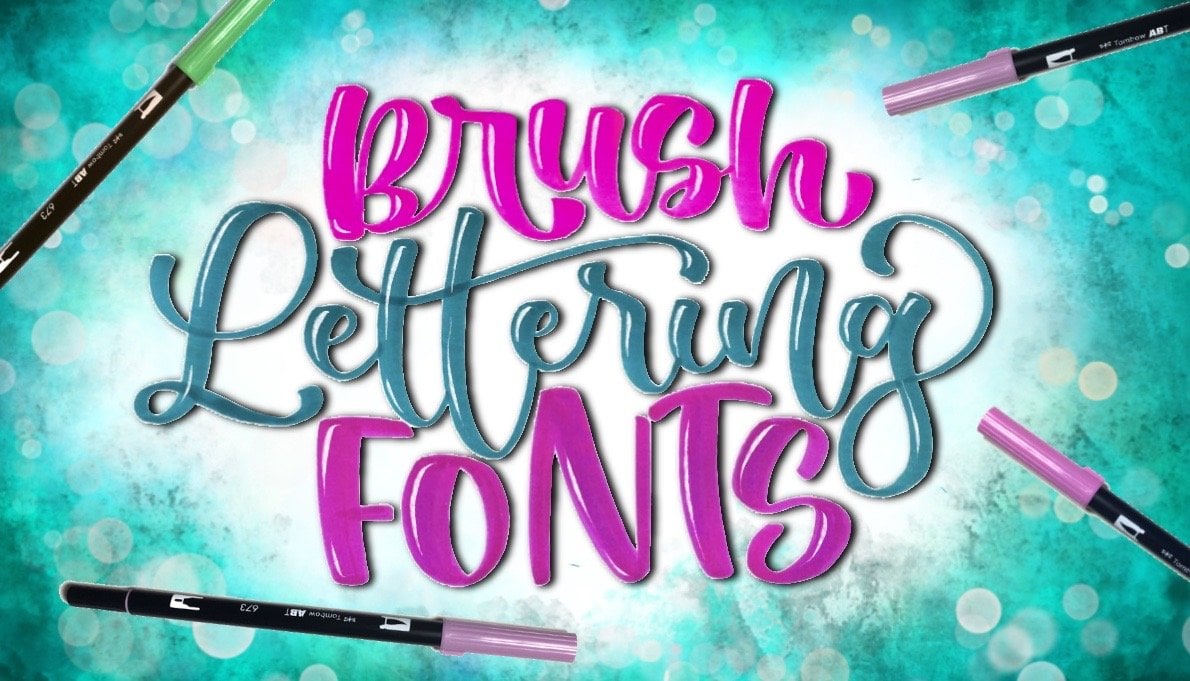
Pinsel-Lettering Schriftarten – Liebe Dein Lettering
In diesem fun, farbenfrohen Kurs von Alyssa (auf Instagram und YouTube als Lyssa Letters) , der du deine Letteringfähigkeiten auf die nächste Stufe bringen kannst. In diesem Handlettering werden wir erkunden, wie du mit einem Pinselstift fachmänner die verschiedenen Buchstabenformen entwerfen kannst!
Perfekt für alle, die mit den Grundlagen der Pinselkalligrafie vertraut sind und die ihre Lettering-Fähigkeiten verbessern möchten. Jede Kurses ist vollgepackt mit Demonstrationen und Beispielen, die dir dabei helfen, während du die wichtigen Elemente von Buchstabenformen lernst und wie du diese Formen von ihrer eigenen Erstellung ändern kannst.
-Kurve von Strichen
-Winkel
-Strichstärke
-Letter
-Höhle
-Loops
-Verbindungszeichen
Als endgültiges Projekt für den Kurs werden Kursteilnehmer:innen ermutigt, ein Kunstwerk zu erstellen, das mehrere einzigartige Schriftarten enthält.
1. Einführung in Pinsel-Lettering: Hallo, da. Willkommen zu diesem Kurs auf Rush Lettering. Schriftarten. Mein Name ist Elissa, und ich bin ein Handschriftkünstler. Möglicherweise erkennen Sie mich von Instagram oder YouTube, wo mein Kontoname „Hören“ lautet. Briefe. Mein eigener Stil zeichnet sich durch super lebendige Farben, viele zusätzliche Verzierungen und lustige Illustration aus. Warum ist jemand wie ich, der so auf Farbe fokussiert ist und eine Geschichte durch meine Hand Schriftzug Artwork erzählt , so leidenschaftlich darüber, einen Kurs über Rush Lettering zu unterrichten? Schriftarten Nun, die Form Ihrer Buchstaben und wie diese Buchstaben miteinander interagieren, ist das Fundament , auf dem alle anderen Elemente gelegt werden. Schriftarten können unterschiedliche emotionale Reaktionen von Ihren Lesern hervorrufen. Ich glaube, dass das Wissen und die Werkzeuge haben, um viele verschiedene Buchstabenformen und Schriftarten erstellen zu können , für jeden Handschriftkünstler auf jeder Ebene unerlässlich ist, egal ob Sie ein Anfänger sind und Sie Ihren eigenen Stil kreieren möchten oder ein Experte und du machst seit vielen Jahren Handschriftzug, um dich davon abzuhalten, von der Verwendung der gleichen Schriftarten immer und immer wieder ausgebrannt zu werden. Aber ich habe festgestellt, dass es nicht viele Ressourcen gibt, für jemanden, der ihre eigene Schrift entwerfen will , die eine ganze Menge verschiedener Schriftarten gelernt werden, ohne Tracing-Blätter zu verwenden oder jemand anderes Handschriftzug zu kopieren . Ich habe diesen Kurs erstellt, um Ihnen eine einfache Möglichkeit zu geben, Buchstaben und Wörter in einfache Elemente zu zerlegen , so dass keine Ablaufverfolgungsblätter oder Kopieren erforderlich sind. Sie können jeden Aspekt von Buchstabenformen wie Kurven, Winkel, Strich, Dicke und Höhe einfach und fachmännisch ändern Winkel, Strich, . Wir werden auch untersuchen. Müssen Sie Ihre Buchstaben in Wörter auf verschiedene Arten kombinieren. Es wird viele Demonstrationen während des Kurses geben, um Ihnen zu zeigen, wie Sie die einzelnen Fähigkeiten anwenden können. Sie werden das Beste aus diesem Kurs herausholen, wenn Sie bereits mit den Grundlagen der Pinselbeschriftung vertraut sind , wie zum Beispiel dicke Strichstriche und dünne Striche, sowie wie Sie einen Pinsel verwenden und halten. jedoch Wenn Siejedochein kompletter Anfänger sind, ermutige ich Sie, diesen Kurs zu nehmen, weil ich in ziemlich viel Detail über die Elemente von Buchstaben gehen . Wenn du mir in sozialen Medien gefolgt bist, solltest du jetzt wissen, dass ich eine Menge anderer Leute Kurse zum Thema Geschick nehme. Teilen Sie, auch, erhöhen Sie meine eigene Wissensbasis über Handschrift und andere Formen der Kunst. Etwas, das ich bei diesen Kursen sehr hilfreich fand, ist es, ein Ressourcenblatt über Dinge zu erstellen , die ich gelernt habe, damit ich zurückblicken kann, dass ich Sie später sehr ermutigen würde , dasselbe für diesen Kurs zu tun. Und wenn Sie sich sehr ehrgeizig fühlen, würde ich Sie einladen, ein Projekt für diesen Kurs zu erstellen, in dem Sie Ihren Namen oder den Namen eines anderen in die Mitte der Seite in einem Fonds schreiben und dann verschiedene Deskriptorwörter oder Dinge schreiben dass diese Person liebt es, diesen Namen in verschiedenen Fonds zu umgeben. Also bin ich sehr aufgeregt, dass du mich heute in diesem Kurs begleiten wirst, lasst uns anfangen. 2. ZUBEHÖR: Es gibt eine sehr große Auswahl an Pinselstiften da draußen, und die Pinselstifte, mit denen Sie Zehenbuchstaben wählen, beeinflussen die Arten von Stilen und Schriftarten, die Sie erstellen können. Und das liegt daran, dass jede Art von Pinselstift eine andere Pinselspitze oder Spitze länger hat und flexiblere Pinselspitzen ermöglicht es Ihnen, breitere Striche zu erstellen. Während Pinselspitzen, die kürzer und weniger biegsam sind, nicht so dick wie unten Striche schneiden können,sind sie in der schneiden können, Lage, eine feinere Linie zu erzeugen. Werfen wir nur einen kurzen Blick auf die Pinselstifte, die Sie mich in diesem Kurs für die größeren Pinselnips sehen , werde ich mit Tom Bo Dual Pinselstifte sowie Künstler geliebt Doppelpinsel Schmerzen. Diese zwei Arten von Pinselstiften haben sehr ähnliche Fässer und nahezu identische Pinselspitzen in Bezug auf Länge und Flexibilität. Ich werde auch gleiche Linie von Pinselstiften verwenden, die eine lächerlich flexible Frische haben, was großartig ist, weil Sie einen wirklich dicken Strich nach unten bekommen können, aber Sie haben nicht so viel Kontrolle über die Dicke Ihrer Striche demonstrieren Sie die kleineren Pinselstifte. Ich benutze die harten und weichen Spitzen des Tom Bo Essens und keine Sasuke. Ich glaube, so sprechen Sie es aus. Wenn ich es nicht richtig ausspreche, lassen Sie es mich wissen. In den Kommentaren dieses Kurses haben diese frischen Freunde einen viel kürzeren Lauf als die Doppelbürste kommt, und sie können sehr feine Linien erzeugen, weil die Feder klein ist. Und für die mittelgroßen Pinselstifte, werde ich Papier Castells verwenden, die ich einfach lieben ihre erstaunlichen. Sie haben eine ziemlich lange Pinselspitze im Vergleich zu den kleineren Pinselstiften, so dass Sie dies einen wirklich schönen Kontrast zwischen den Abwärtsstrichen und den Aufwärtsstrichen schaffen können , die ich einfach liebe. Sie sind jedoch nicht in der Lage, so weit wie die Tom Bögen oder ICO-Linien zu bekommen, obwohl. Fühlen Sie sich frei, um die Art von Pinselstiften zu verwenden, die für Sie am bequemsten sind. Aber unabhängig davon, welche Art von Pinselstiften Sie verwenden, ist die Art von Papier, die Sie wählen, extrem wichtig. Um Ihre Pinselstifte zu bewahren, möchten Sie Ihren Pinsel nicht ausfransen, und der beste Weg, dies zu tun, ist, auf Lee das glatteste Papier zu verwenden, das Sie eingegrenzt Marker Papiere eine gute Option, sowie HP Premium £32 Papier, das schön und dick ist, so dass die Tinte nicht durchblutet. Und wenn Sie Glück haben, finden Sie vielleicht ein schönes Tagebuch, das super glattes Papier wie dieses hat, das ich früher meine eigenen Hände geübt habe. Schriftzug oh so glatt. Ich liebe es. Aquarellpapier und Mixed-Media-Papier sind ziemlich grob und können dazu führen, dass die Pinselnips umrahmt oder schnell sind. Aber es gibt eine gute Option. Wenn Sie eine Menge Mischung mit Wasser machen, würde ich Sie sehr ermutigen, die PDF-Formulare zu drucken, die als Ressource für diesen Kurs verfügbar sind . Es gibt gefütterte Blätter in verschiedenen Größen, ideal für Beschriftungen mit unterschiedlich großen Pinselspitzen. Und wieder, stellen Sie sicher, dass Sie diese Seiten auf das glatteste Papier drucken, das Sie wie Laserdruckerpapier beschränkt haben . In Ordnung, lassen Sie uns in die erste Lektion des Kurses gehen, wo ich eine der Grundlagen für die Erstellung verschiedener Buchstabenformen vorstellen werde 3. Downstroke: in dieser Lektion untersuchen wir die verschiedenen Formen von Strichkurven nach unten, sodass die erste Grundform eine gerade Linie ist. Die 2. 1 ist eine C-förmige Kurve in dieser Richtung. Die nächste Kurve ist in die entgegengesetzte Richtung geformt, und die letzte ist eine S-förmige Kurve. zunächst einen Blick darauf werfen, Lassen Sie unszunächst einen Blick darauf werfen,wie diese Kurven auf einen Buchstaben anwenden können, der ein A-Zentrum wie dieses h hier hat . Ich nehme den Brief. L zwei verwendet ihr Beispiel, nur weil es das einfachste ist. Es hat nur diesen einen Schlag nach unten. Die erste Option wäre, nur einen geraden Strich für die L. zu machen Okay, also wäre die zweite Grundform, dein L mit einem kleinen bisschen einer Kurve wie diese zu schreiben . Es ist also keine gerade Linie mehr. Das ist Nummer zwei. Wir können auch die dritte Kurvenform für jetzt machen, die Sie hier sehen können. Es ist kein sehr häufiges geformtes fremdes l, besonders wenn Sie in Skript schreiben und Schleifen verwenden, aber es kann getan werden, und ich würde keine s förmige Kurve für L tun, weil es nur so aussehen würde, wie es s, so haben wir eine Art drei grundlegende Optionen für diese l Schauen wir uns an, wie wir mehr Variationen der zweiten Kurvenform machen können. Zum Beispiel kann ich den Brief mit einem Bordstein oben schreiben und ihn dann gerader nach unten machen . Und hier ist, wie das aussehen würde, wenn ich es mit einem Luke zeichnen würde. Eine andere Möglichkeit wäre, gerade an der Spitze zu tun und dann mehr gebogen nach unten so. Und wenn ich den Luke hinzufügen würde, würde es so aussehen. Und dann können wir ein L machen, wo der gesamte Strich abgerundet ist und wir können die abgerundete Form in verschiedenen Graden machen , zum Beispiel, wirklich subtil, wie dieser, oder noch mehr abgerundet. Beachten Sie jedoch, wie wichtig die Lesbarkeit ist. Wir wollen nicht, dass unsere Leser denken, dass wir ein C anstelle eines L schreiben. Also haben wir diese spezielle Kurvenform ein wenig aufgeschlüsselt, aber wir können tatsächlich noch mehr Variationen davon machen. Nehmen wir zum Beispiel den Buchstaben H. Sie können die verschiedenen Variationen machen, wie ich zuvor erwähnt habe, in unterschiedlichem Maße. Zum Beispiel können wir die Oberseite so machen, dass Wörter sehr gekrümmt oben und dann gerader unten. Oder wir könnten eine viel kleinere Kurve an der Spitze machen und sie unten gerade sein lassen. Aber Sie können immer noch sehen, dass es eine Kurve an der Spitze. Ebenso, wenn wir es gerade an der Oberseite des Abwärtsstrichs und dann unten gekrümmt machen wollen ,können wir es zu einer kleinen Kurve am unteren Rand machen. , Oder wir können es zu einem sehr großen Bordstein am Boden machen. Denken Sie daran, dass je mehr Sie eine Kurve zu diesem Abwärtsschlag des Alters machen, sie dehnen die Grenzen dieses Alters. Stellen Sie nur sicher, dass es als H. erkennbar bleibt. Ich denke, es ist erwähnenswert, dass Sie die Abwärtsstrichkurve davon machen können. Ein Donner in dem Buchstaben H geht auch in diese Richtung. Sie können hier Option Nummer drei mit dem H. verwenden ich würde H wahrscheinlich nicht so machen. Das ist sehr merkwürdig. Aber nochmal, ich will euch keine Regeln geben, wie ihr eure Briefe machen könnt. Aber nochmal, Hier geht es darum, dass du deinen eigenen Stil findest. Sie können es hilfreich finden, einen oder zwei dieser a Mittelbuchstaben zu wählen und zu sehen, wie viele verschiedene Möglichkeiten Sie sie schreiben können. Werfen wir einen Blick auf Briefe wie diese. Warum das eine D-Mittellinie haben? Nehmen wir den Buchstaben J als erstes Beispiel. Option Nummer eins wäre, einen relativ geraden Strich nach unten zu machen. Kann auch die dritte Kurvenform für den Buchstaben J verwenden, und wir können unsere S-förmige Kurve, die ich wirklich geliebt. Sie werden bemerken, dass ich Nummer zwei nicht für das J gemacht habe, weil Jay einfach nicht diese Art von Kurve hat . Und das gilt auch für G und warum. Und es liegt daran, dass dieser Aufschlag hier herumkommt und genau wie wir es mit den A-Sender Down Strichen getan haben, können wir verschiedene Variationen dieser Kurven in unserem D-Zentrum nach unten Starks machen. Also, zum Beispiel, lassen Sie uns auseinanderbrechen dies'll hier, so kann ich an der Spitze gerundet und gerade an der Unterseite für gerade an der Spitze und abgerundet an der Unterseite tun. Oder wir könnten einfach in J. gerundet machen und so wie wir es mit den achten Mittelbuchstaben gemacht haben, die Sie machen können. Dies ist abgerundet, wie Sie wollen, so lange es immer noch wie ein J aussieht. Und wenn wir die s förmige Kurve machen, können Sie es sehr subtil machen. Oder Sie können die s geformte Kurve noch dramatischer machen. Ich werde ein G als Beispiel verwenden, weil es mit G einfach natürlicher aussieht als mit Jay. Er ist ein Brief, dass Sie den Abwärtsstrich natürlich gerade gehen lassen können. Und dann, in Vernichtung oder Zerstörung, tun Sie es. 1243 Ich habe es nicht mit einer s förmigen Kurve ausprobiert. Ein bisschen komisch. Ich denke, es liest sich immer noch wie ein P, aber es ist sehr stilisiert. Und der Buchstabe Q hat wirklich nur die Möglichkeit, einen geraden Strich nach unten zu machen, oder es kann Nummer zwei sein . Und mit diesen Abwärtsstrichen können Sie sie sehr abgerundet machen. Sie können es oben abgerundet und gerader unten oder gerade oder oben und unten abgerundet machen. Die Abwärtsstrichkurven-Shapes gelten auch für die Abwärtsstriche von Großbuchstaben, sodass Sie einen geraden Strich nach unten ausführen können. Man könnte sagen, dass ich es wirklich gewohnt bin, gekrümmte Striche zu machen, weil ich versucht habe dort eine Kurve zu machen. Sie können einen Bordstein in diese Richtung machen. Sie können einen Bordstein in die andere Richtung machen, oder Sie können eine s förmige Kurve genau so machen. Wenden wir das, was wir gerade besprochen haben, auf das Wort get an. Ich werde dies auf ein paar verschiedene Arten schreiben, unter Berücksichtigung der Form der Abwärtstrichkurve im D-Sender aus dem G und dem A-Zentrum des T Also zuerst, schreiben wir es mit genauso geraden nach unten Striche für diese beiden Elemente, wie ich es machen kann. Das ist also ein Blick, der die Abwärtsstriche so gerade macht, wie ich sie vielleicht machen könnte. Sie können aus diesem Beispiel sehen, dass nur durch Ändern der Form der Kurve für unsere A-Zentren und D-Mittelpunkte Weg können mehrere verschiedene Stile erstellen. Ich möchte Sie ermutigen, Ihr eigenes Wort auszuwählen, das ein Zentrum und D-Zentrum darin hat und sehen wie viele verschiedene Möglichkeiten Sie es schreiben können. Unter Berücksichtigung all dessen, was wir in dieser Lektion besprochen haben. 4. Kleine Downstroke: So haben wir längere Abwärtsstriche wie ein Absender und D-Absender diskutiert. Lassen Sie uns nun über diese kürzeren Abwärtsstriche für Buchstaben sprechen, die eine ovale Form haben , die einen Abwärtsstrich haben, der von einem kleinen Aufschlag wie diesen vorausgeht. Die Kurve dieses Abwärtsstrichs kann entweder etwas gerade sein, oder es kann sich um eine beliebige Variation der gekrümmten Nummer zwei handeln. Achten Sie auf die verschiedenen Möglichkeiten, wie ich diese Kurve machen kann. Sie können feststellen, dass ich die Kurve mehr oder weniger oben umgeben oder mehr oder weniger unten abgerundet machen kann . Die kleinen Abwärtsstriche in diesen Buchstaben wie der Stamm auf dem M und A und A könnten möglicherweise als gerade Linie oder Kurven zwei und drei geschrieben werden. Mal sehen, wie das aussehen würde, wenn wir den Buchstaben n nehmen und die Krümmung des Stiels ändern . Die Buchstaben B und P haben einen sehr ähnlichen kleinen Abwärtsstrich, und dieser kleine Abwärtsstrich kann die Form einer geraden Linie wie Nummer eins annehmen, oder er kann auf verschiedene Arten als Kurve Nummer drei geschrieben werden. Unsere letzte Gruppe kleiner Abwärtsstriche umfasst den zweiten Abwärtsstrich der Buchstaben H m ein Ende sowie den dritten Abwärtsstrich des Buchstabens M hier mit dem Buchstaben N. Ich schreibe diesen zweiten Abwärtsstrich mit einer geraden Linie. Als Nächstes mache ich einen Abwärtsstrich wie Kurve Nummer zwei. Und schließlich könnten Sie diese Kurve wie Nummer drei machen, und ich habe am Ende diese Kurvenform ein zweites Mal gezeichnet, nur um dieses Beispiel ein wenig deutlicher zu machen . 5. Upstroke: die gleichen vier Grundformen für die Abwärtsstrichkurven. Wenden Sie auch die Aufstrichkurven an. Sie haben eine gerade Linie, haben eine Kurve, die in diese Richtung geht, in Zerstörung und eine s geformte Kurve. Also zuerst, lassen Sie uns darüber sprechen, wie die Lieferungen Zehenbuchstaben, die einen spitzen Winkel haben, ausgehend von einem Abwärtsstrich wie diesem, der ihn und P C Weg umfassen würde, diesen Abwärtsschlag haben. Und dann geht da noch der scharfe Winkel hoch. Also schauen wir uns den Hummer speziell an. Dasselbe mit Schlüssel. In manchen Fällen schreibt es nicht jeder so. Es gilt auch für K. Wenn Sie es so schreiben, wo Sie diesen Abwärtsschlag haben und dann den spitzen Winkel direkt dort in den Aufschlag gehen sowie ein Visum, und dann haben Sie H I. M. Und Ende alle mit dem gleichen Winkel. Nehmen wir zum Beispiel den Buchstaben B . Also mit dem Buchstaben B und den meisten dieser Buchstaben, in der Tat, werden Sie wahrscheinlich nur sehen, dass dieser Aufschlag hier mit einer geraden Linie oder Kurve in dieser Richtung geschrieben wird. Wenn wir zum Beispieleine gerade Linie machen würden,würde es etwas so aussehen, wenn wir es in diese Richtung tun würden. zum Beispiel Wenn wir zum Beispieleine gerade Linie machen würden, Es gibt eine ganze Reihe von verschiedenen Optionen, basierend darauf, wie gerundet wir wollen, dass diese Kurve sein wird. Und Sie können sich wirklich frei fühlen, mit den Formen dieser Kurven herumzuspielen und zu versuchen, zu sehen welche Formen der Abwärtsstrichkurven Sie mit den Formen der Aufwärtskurven mögen. Ich möchte auch erwähnen, dass diese s geformte Kurve manchmal verwendet werden kann. Oder wenigstens habe ich es gesehen. Mit Buchstaben wie Dies wäre, könnte man sehen, dass jemand so etwas macht, wenn es sehr stilisiert ist. Wenn es im Kontext eines Wortes steht und der Rest ihrer Buchstaben auf diese Weise etwas stilisiert ist, dann ist es eine vollkommen gute Wahl, solange es hier lesbar bleibt. Ich habe den Buchstaben n genommen und ihn auf sechs verschiedene Arten geschrieben, indem ich verschiedene Kurven der Aufwärtsstriche verwende. Können Sie die Form der Kurve für jede einzelne sehen? Werfen wir nun einen Blick auf eine andere Gruppe von Buchstaben. Dieses Mal werden wir uns Buchstaben ansehen, die einen fließenden Übergang zwischen dem Abwärtsstrich und dem Aufschlag haben. Es gibt eine ganze Reihe von Briefen in dieser bestimmten Gruppe beteiligt, die diese Form haben. Du könntest die a c D. Etcetera sehen . Sie alle haben diesen Abwärtsschlag, gefolgt von einem Aufschlag, und es gibt einen fließenden Übergang zwischen. Hier können Sie sehen, wie es aussehen würde, wenn ich diesen Schlaganfall relativ gerade machen würde, wie die erste Option hier. Und Sie können diese dritte Option tun. Und es gibt verschiedene Formen, die Sie verwenden können, um diese Kurve zu machen, die in einer Minute übergehen wird. Und Sie können sogar eine S-förmige Kurve machen. Obwohl Sie wirklich vorsichtig sein müssen, dass es immer noch aussieht wie der Brief, den Sie zu schreiben versuchen . Also, wie versprochen, werden wir diese Kurven ein bisschen mehr aufbrechen, um etwas systematischer darüber zu werden. Und wir werden den Buchstaben A für diesen Teil verwenden. Also für diese zuerst, ein gezeichnetes Oval mit einem Aufschlag, der diese Formkurve hat und dann dieser nächste Aufschlag im Oval wird nur ein bisschen weniger abgerundet sein, wie man hier und dann diese 3. 1 hier im Oval sehen kann, der Aufschlag ist noch weniger abgerundet. Also mache ich die Form näher und näher an einer geraden Linie. Dieser nächste hier ist der Aufschlag eine gerade Linie, und dann sind die letzten beiden Jungfrauen s geformte Kurven. Und hier ist, wie alle von ihnen aussehen, wenn ich den Stamm des A hinzufüge Nun werfen wir einen Blick darauf, wie das in einem Wort hier funktionieren würde Ich habe die Worttasche genommen und Sie können sehen, ich habe die Krümmung der Aufwärtsstriche geändert. Also in der ersten Version, sind sie ziemlich abgerundet. Und in der zweiten Version habe ich die Aufschläge eher eine gerade Linie gemacht. Es gibt ein paar Buchstaben, die Striche haben, die horizontale Bedeutung haben. Anstatt nach oben und unten zu gehen, gehen sie von Seite zu Seite. Zum Beispiel mit dem Buchstaben T können Sie mit dem Buchstaben Tden horizontalen Strich hier sehen. Hier habe ich geschrieben, dass Strich eine gerade Linie ist, aber es gibt andere Optionen. Zum Beispiel können Sie es wie eine Welle oder eine S-förmige Kurve auf der Seite formen, und Sie können dies in beide Richtungen tun. Sie können sie auch zu einer U-förmigen Kurve oder einer umgekehrten U-förmigen Kurve machen. Horizontale Striche für den Tee können sehr gekrümmt werden, um sie für eine sehr Kurven und abgerundet. Also, zum Beispiel, dieses werde ich sehr subtil tun. Ich denke, das und das hier werde ich dramatischer machen, also wirst du wirklich sehen, dass es ganz um ihn herum ist. Und natürlich könnte man überall zwischen denen tun, die der Buchstabe auch hat, ah, ah, horizontalen Strich, die Sie uns eine gerade Linie schreiben können, oder Sie können es gekrümmt und dasselbe für die Buchstaben e Sie können schreiben, dass horizontale Striche eine gerade Linie, oder Sie können es ein bisschen wie eine Kurve geben. 6. Loops: Okay, es ist Zeit, über Schleifen zu sprechen. Loops machen so viel Spaß und sie fügen so viel Charakter zu Ihren Briefen. Also lasst uns direkt eintauchen. Wir beginnen hier mit unseren schönen A-Mittelbuchstaben, die ich nicht mit Luke auf der A-Mitte geschrieben habe, und das ist eine vollkommen gute Option. Du musst keine Schleife benutzen, aber ich werde dir zeigen, wie sie aussehen würden, wenn sie Gruppen hätten. Ich habe den Buchstaben T nicht mit einer Schleife geschrieben, aber es kann sein und ich werde euch zeigen, dass später die Schleifen, die in eine Mitte nach unten führen , entweder vertikal oder horizontal verändert werden können. Wenn Sie es längst nicht bemerkt haben. Ich benutze den Buchstaben H oft als Beispiel, weil er wahrscheinlich mein Lieblingsbrief an eine 11. Aber hier werde ich nur die Schleife kürzer und kürzer machen, während ich mitmache. Ich kann die Schleife auch ändern, indem ich ihre Höhe konsistent halte, sie aber nur breiter und breiter mache , während ich mitmache. Und wenn du dachtest, du könntest dasselbe mit den Senderschleifen machen, naja, du hattest Recht. Sie können sie kürzer oder länger oder dünner oder breiter machen, etwas, das ich zu Dio liebe, mit meinen DIY-Mittelschlaufen wie diese ist nicht nur eine regelmäßige ovale Form wie das, was Sie hier sehen, sondern um uns tatsächlich zu machen etwas Besonderes geformt, indem Sie die Richtung der Kurve ändern, wie Sie sehen, wie ich es hier tun. Es ist wirklich treffen, und wieder ist es immer in Ordnung, keine Schleife zu verwenden. Manchmal ist weniger mehr. Zusätzlich zu den A-Mittel- und D-Mittelschleifen gibt es eine Reihe von Buchstaben, die oft mit ihren eigenen speziellen Gruppen geschrieben werden. Zum Beispiel hat der Buchstabe B eine Schleife, die oft verwendet wird, die vom kleinen Abwärtstrick Sie zum Austrittsstreifen führt und Sie können sehen, dass es optional ist. Sie müssen es nicht verwenden, und dann, wenn Sie es verwenden, können Sie es eine Vielzahl von verschiedenen Größen machen. Es kann wirklich klein sein, oder es kann ziemlich groß sein, sogar bis zu dem Punkt, an dem die Schleife über den langen Strich kreuzt. Wie Sie sehen, wie ich hier geschrieben habe, geht Lukken unter die Grundlinie, wie Sie mich hier schreiben sehen, und es kann sogar unter die Grundlinie gehen und dann wieder nach oben kommen und durchqueren die lange Mitte unten. Genau so hat der Buchstabe P eine fast identische Schleifen, die von dem kurzen Abwärtstrick geschrieben werden könnten, der in den Austrittstrich geht. Und Sie können sehen, dass ich es mit einer Vielzahl von verschiedenen Größen hier jetzt auf einen meiner absoluten Lieblingsbuchstaben geschrieben habe , um Schleifen mit dem Buchstaben O zu verwenden. Also wieder, Sie müssen keine Schleife verwenden, oder Sie können eine kleine für etwas größer oder ein noch größeres. Und eine andere coole Sache, die ich gerne mit meinen Schleifen mache, ist es, ihn über den anfänglichen Abwärtstrick zu überqueren , wie Sie hier sehen, und Sie können wirklich weit damit gehen, oder Sie müssen nicht einmal die Schleife überhaupt mit dem ersten unten verbinden. Ich liebe es auch, dem Buchstaben Schleifen hinzuzufügen, sind Sie können eine kleine Schleife oder eine sehr große Schleife hinzufügen, solange der Leser immer noch weiß, dass es die Schleife ist, die oft mit dem Buchstaben s verwendet wird, der in den Ausgang führt. Stroke ist im Grunde die gleiche wie die Schleife für die Buchstaben B und P verwendet jetzt, wo wir uns einige der häufigsten Buchstaben angesehen haben , die mit Schleifen geschrieben werden. Werfen wir einen Blick auf den Rest des Alphabets und sehen, welche anderen Buchstaben Schleife überprüft werden können . Ich glaube nicht, dass das ein Wort ist. Ich erfinde das. Das ist ein cooles Wort. Ich habe voran gegangen und Briefe gruppiert, die ähnliche Arten von Schleifen haben. Diese Gruppe Hier sind Briefe, Fakten. Sie können im Grunde eine winzige kleine Schleife vor einem Abwärtshub machen. Also, zum Beispiel, wenn ich den Buchstaben I machen würde, wäre es eine kleine Schleife mit dem Abwärtsstrich so. Und alle diese Briefe hier haben ein ähnliches Muster mit em. Und sie haben diesen Luke. Warum, Sie etcetera Dinge nächste Gruppe von Buchstaben, im Grunde haben alle diese ovale Form, und sie haben eine kleine Schleife, die hineingeht, und dann können Sie verbinden, was Sie wollen, mit ihm. Es ist also ein es würde so aussehen. Die Buchstaben F K Q. Konfronts wirklich interessant heute Abend. Liebe, diese Schlaufen in meinem eigenen Handschriftzug zu verwenden. Sie müssen nur sicherstellen, dass es lesbar bleibt. Manchmal sehen die Leute diese Briefe und keine Ahnung, was sie sind. Was Sie sehen können, ist, dass es dieses Extra genau hier gibt, da dieser Aufschwung über diesen 'll lange nach unten Schlaganfall kommt . Also haben wir einen Abwärtshub und dann, sagen wir, viertes E K würde normalerweise so kommen. Und wenn dieser Abwärtsschlag diesen Punkt hier trifft, würde er stattdessen wieder herauskommen. Wir gehen die Regeln, den Strich nach unten und machen Weg. Tun Sie das Gleiche für die f hier. Kommen Sie so runter, anstatt zu springen, wenn es den Abwärtsschlag trifft, geht es schneller, wie Thetis, und wir tun genau das Gleiche für den Brief. F: Also machen wir unseren D-Center-Down-Hub. Und dann, anstatt den Abwärtsstreifen abzuprallen, gehen wir durch und erschaffen diesen Luke. Sowohl V als auch W können mit einer Schleife geschrieben werden, die vom letzten Aufschlag des Buchstabens in den Ausgangsstrich geht . Und schließlich haben wir den Buchstaben P , der hier allein steht, dass man nach diesem Abwärtsschlag, anstatt wieder nach oben zu springen,kann wieder nach oben zu springen, man sich einfach dort bewegen. Ich hoffe, Sie sind nur ein Z aufgeregt, Schleife. Wenn ich Ihre Briefe jetzt, wie ich bin 7. Winkel und Neigung: der Winkel, in dem ein Strich ausgerichtet ist, ist ein weiteres wichtiges Element von Buchstaben. Vielleicht wäre das offensichtlichste Beispiel dafür mit einer Tallis isierung für jeden Buchstaben es einen Slam gezeichnet hat. Möglicherweise finden Sie es hilfreich, die von mir bereitgestellten PDF-Dateien zu verwenden, die parallele Linien in verschiedenen Winkeln gezeichnet haben, so dass Sie verschiedene Kursivstufen üben können , wenn Sie Ihre Buchstaben schräg schreiben . Typischerweise sind Abwärtsstriche alle parallel zueinander, was Sie so geübt wurden, wie ich es hier tue. Und wenn Sie sich wohl fühlen, Vorräte selbst zu ziehen, können Sie sich bis zu Buchstaben und Wörtern arbeiten. Die Buchstaben des Wortes schräg zu schreiben ist sicherlich ein eleganter Stil, aber es gibt auch viele andere Optionen. Lassen Sie uns untersuchen, wie wir die Winkel der diff'rent Striche innerhalb von Buchstaben ändern können, um jedem Buchstaben einen anderen Stil zu geben . Wir beginnen, indem wir horizontale Striche betrachten, zum Beispiel in den Buchstaben R und E. Hier zeichne ich den Buchstaben R mit einem horizontalen Querstrich nach unten. In diesem nächsten Beispiel ist der horizontale Strich parallel zum unteren Rand der Seite oder gerade quer und eine andere Möglichkeit besteht darin, den horizontalen Strich in einem aufwärts liegenden Winkel zu bewegen. Der horizontale Strich im Buchstaben e kann auch in verschiedenen Winkeln geschrieben werden. Wir können auch Striche in verschiedenen Winkeln aufschreiben, um Buchstaben, verschiedene Stile zu geben . Zum Beispiel habe ich hier das Wort Hand auf drei verschiedene Arten geschrieben, und alles, was ich getan habe, ist, dass ich den Winkel des kleinen Abwärtsstrichs geändert habe, so dass Sie hier sehen können. Was ich getan habe, ist, dass ich meine Daunenschläge ziemlich hoch und runter gemacht habe. In der zweiten Version des Wortes Hand schrieb ich die Abwärtsstriche, die von rechts nach links und in der endgültigen Version dieses Wortes angeln . Ich habe diese kleinen Abwärtsstriche geschrieben, die in die andere Richtung ausgerichtet sind, so dass sie von links nach rechts gehen , während sie nach unten gehen. Also jetzt, wenn man sich alle drei zusammen ansieht, sollte der Unterschied offensichtlicher sein. Ändern des Winkels des Stammes auf die Buchstaben Sie und warum gibt die Buchstaben ein ganz anderes Aussehen, wie Sie hier sehen können, finden Sie es vielleicht nützlich, ein Wort für einfache wählen. Ich wählte das Wort Mama und spiele herum, wie Sie die Winkel Ihrer Abwärtsstriche machen können . Also in der ersten Version habe ich meine Daunenschläge ziemlich hoch und runter gemacht. Was ich jetzt tue, ist für meine kleineren Abwärtsstriche. Ich versuche, sie so zu orientieren, dass sie von links nach rechts gehen, während sie nach unten gehen und dann in der letzten Version versuchen, meine Abwärtsstriche so zu orientieren, dass sie von rechts nach links gehen. Wir können auch über den Winkel unserer Aufwärtsstriche nachdenken, zum Beispiel, dass kleine Aufwärtsbewegung nach dem Mittelstamm. In dem Buchstaben H können Sie sehen, dass ich diesen Aufschlag in verschiedenen Winkeln gezeichnet habe, und es gibt dem Buchstaben ein ganz anderes Aussehen. Und hier ist, wie das aussieht, wenn wir eine Schleife und ein bisschen Runde hinzufügen, dass ein Mittelstand mit der Acht und das gleiche Prinzip gilt für jeden Buchstaben, der einen Aufschlag hat . Werfen wir einen Blick auf dieses Beispiel. Mit dem Wort blinzeln, werden Sie in der Lage sein zu sehen, dass ich die Aufwärtsstriche in jeder Version des Wortes in einem anderen Winkel geschrieben habe , und wenn Sie nur dieses ein Detail ändern, wird jedes Wort ein wenig anders aussehen. 8. Strichstärke: Nehmen wir uns ein paar Minuten Zeit, um über die Strichstärke zu sprechen. Was mir beigebracht wurde, war, wenn man einen Niederschlag macht, macht man ihn dick, und wenn man einen Aufschlag macht, macht man ihn dünn. Aber was bedeutet das? Denn wenn du darüber nachdenkst, sollte ich theoretisch in der Lage sein, viele verschiedene Verstand eines Abwärtsschlags zu machen. Zum Beispiel, ich kann wirklich halten meine Bürste, war weit unten auf dem Lauf und drücken ziemlich hart und bekommen eine sehr, sehr dicke Linie, und dann kann ich ein wenig weniger machen diese 'll weniger. Aber all diese könnten Sie als den Abwärtsschlag betrachten. Sie könnten alle dicker sein als der Aufschwung. Das ist wirklich die einzige Voraussetzung, einen dickeren Abwärtshub zu haben. Und ich kann mit der Spitze sehr feine Linien machen, besonders wenn ich es etwas senkrechter zu meinem Papier halte. Und ich kann auch sehr, sehr dicke Linien machen . Also könnte der Unterschied in der Dicke zwischen meinem Abwärtshub und meinem Aufschlag theoretisch so groß sein. Und ich könnte auch ein Stück machen, bei dem der Unterschied zwischen der Dicke in meinem Daunenschlag und meinem Aufschlag extrem klein ist. Also vielleicht ist ein Abwärtsschlag so dick und dann ist ein Aufwärtsschlag das Ding. Hier ist ein Beispiel, wo ich den Tom Bo paar Tag mit dem harten Tipp verwendet, um das Wort upstroke auf drei verschiedene Arten mit drei verschiedenen Verstand der Aufwärtsstriche zu schreiben . erste Beispiel an der Spitze hat die dünnsten Schläge, und ich habe erstellt, dass, indem ich weniger Druck, als ich meine UPS LKW machte, dass ich in der Lage war, eine sehr dünne Linie zu erreichen. Für das zweite Beispiel hier habe ich den gleichen Druck für meine Abwärtstriche verwendet wie für das erste Beispiel, aber für meine Aufwärtsschläge habe ich etwas mehr Druck verwendet, also sind sie etwas dicker, und dieses letzte Beispiel hat die breitesten Aufwärtsstriche der drei, weil ich den größten Druck ausgeübt habe, um die Aufwärtsstriche zu erzeugen. Ich denke, es ist ein bisschen einfacher, den Unterschied in dieser Nahansicht zu sehen. Ich habe die gleiche Übung mit einem Tom Bo Dualpinsel Wortspiel gemacht, und weil die Tom Bo Doppelbürste hat eine längere und flexiblere Frische als der Tumor ein paar Tage frische Verbrennung, konnte ich mehr Variation in der Peitsche der Aufwärtsstriche bekommen. Etwas anderes in Linien zu halten, wenn wir über das Thema Strichstärke sind, ist, dass wir nicht brauchen, um unsere Abwärtsstriche und Aufwärtsstriche selbst während des gesamten Strichs zu machen. Ich kann einen ziemlich gleichmäßigen Abwärtsstrich wie den machen, wo die Breite der Oberseite und der Mitte und der Unterseite ziemlich gleichmäßig ist. Aber ich kann auch ein bisschen so verjüngen, so dass es oben dicker anfangen kann und unten dünner wird. Ich kann auch etwas dünner anfangen, dicker werden und dann wieder dünner werden. Also offensichtlich diese Luft nicht perfekt. Ich mache sie jetzt wirklich langsam, und ich mache sie nicht im Zusammenhang mit einem Brief, also sehen sie wahrscheinlich ein bisschen seltsam aus. Wenn Sie es jedoch einmal im Kontext eines Briefes sehen , wird es viel mehr Sinn machen, und das werden wir in einer Minute erreichen. Eine andere Möglichkeit ist, beginnen Sünde und dann nur schrittweise dicker in Richtung unten. Also werde ich den Buchstaben H als Beispiel verwenden, weil es meine Lieblingsbriefe sind, und jetzt werde ich versuchen, es ziemlich gleichmäßig zu halten, also hat mein Daunenschlag nicht einmal mit diesem Temperament der Verjüngung. Also fangen wir an und dann hebe ich meinen Stift etwas hoch. So wird es unten etwas dünner als oben. Und ich werde das Gleiche für diese umgekehrte dich so tun. Manchmal mache ich das auch mit dem Ass unter Abwärtsschlag. Mal sehen, ob ich das jetzt tun kann. Es ist nicht super einfach auf Befehl, und dann können Sie immer, natürlich, Ihre Briefe und dann diesen. Ich werde versuchen, dies zu tun, ohne die Schleife zu verwenden, weil ich denke, es ist einfach einfacher für mich, ohne die Schleife zu dio. Also, das sind alle verschiedenen Optionen, die Sie dio können. Werfen wir einen Blick darauf, wie das funktioniert. In einigen anderen Buchstaben ist der Buchstabe links oben am dicksten, und er verjüngt sich nach unten. Der Buchstabe in der Mitte ist sogar durchgehend, und der Buchstabe rechts ist unten am dicksten. Jetzt werde ich das Wort dunkel nehmen und mit verschiedenen Möglichkeiten experimentieren, um die Linienstärke zu variieren . In dieser ersten Version habe ich versucht, den Strich fair zu halten, auch in Bezug auf die Dicke durchgehend. Und in der zweiten Version verjünge ich es, also ist es oben dicker und unten dünner. Und in dieser letzten Version tue ich mein Bestes, um es von dünner der beiden oberen, dicker am unteren Ende des Abwärtsstrichs zu machen. Ich würde Sie auf jeden Fall ermutigen, ein oder zwei Wörter zu wählen und mit verschiedenen Arten zu spielen, um diese Worte zu schreiben, indem Sie die Dicke Ihrer Striche variieren. Du könntest sich verjüngen. Du bist unten Striche, wie ich es hier tue. Sie könnten Ihre Abwärtsstriche durchgängig konsistent halten. Sie könnten Ihre Schläge dünner oder dicker machen. Was auch immer für Sie richtig ist, haben Sie einfach Spaß damit und dann fahren wir mit der nächsten Lektion fort. 9. Höhle: Alles klar, Leute. Zeit, über das eine Element der Buchstabenformen zu sprechen, die meiner Meinung nach den größten Einfluss auf das, wie ein Brief aussieht, erzeugt. Und das ist eine Buchstabenhöhe. Der einfachste Weg, die Buchstabenhöhe zu ändern, besteht darin, die X-Höhen zu ändern, die sich auf die Höhen kleiner, Kleinbuchstaben bezieht , die Sie sehen können, dass ich hier mit dem Wort Pflege gemacht habe. Ich habe verschiedene X Höhen gemacht und Sie können sehen, dass die Buchstaben größer und größer werden. Eine andere Möglichkeit, die Höhe Ihrer Buchstaben zu ändern, besteht darin, die X-Höhe konsistent zu halten. Aber um die Höhe Ihrer A-Mittelbuchstaben zu ändern, wie ich es hier mit dem Wort groß getan habe, kann man sehen, dass ich wirklich klein angefangen habe, wurde ein bisschen größer, wirklich groß und sogar bis zu dem Punkt, wo es fast absurd aussieht, wie groß diese ein Absender . Und Sie können dasselbe tun, indem Sie die Größe Ihrer D-Absender ändern, aber die X-Höhe gleich halten. Also jetzt hier ist, wo die Dinge wirklich Spaß machen. Jeder Buchstabe besteht in der Regel aus mehr als einem Strich, also können wir tatsächlich darüber nachdenken,die Höhe des Anfangs und des Endes jedes Strichs innerhalb jedes Buchstabens zu ändern, es wird irgendwie kompliziert, Jeder Buchstabe besteht in der Regel aus mehr als einem Strich, also können wir tatsächlich darüber nachdenken, die Höhe des Anfangs und des Endes jedes Strichs innerhalb jedes Buchstabens zu ändern , es wird irgendwie kompliziert, aber lassen Sie es uns zusammenbrechen, indem wir nur einen Buchstaben betrachten. Zuerst fangen wir mit dem Buchstaben I an, weil er nur einen Abwärtsstrich hat. Wir haben also diesen obersten Punkt hier , der der Beginn des Abwärtsstrichs ist, und beziehen sich auch auf diese als die X-Höhe sowie diesen Punkt hier, wo der Abwärtsstrich endet und sich in den Austrittsstrich verwandelt. Und das ist die Grundlinie. Wenn wir die Höhen von einem dieser beiden Punkte ändern, wurden im Wesentlichen entweder die Grundlinie oder die Erregung oder beides geändert . Werfen wir einen Blick darauf, wie das funktioniert. In einem anderen Brief, dieses Mal, wenn wir uns den Brief ansehen , der noch ein paar Striche in dem Buchstaben I hier hat, werden wir uns den Anfang des ersten Abwärtsschlags ansehen. Dann schauen wir uns den Ort an, an dem der Abwärtsschlag endet, und dann beginnt der Aufschlag. Dann schauen wir uns den Ort an, an dem der Aufschlag endet, dann den Anfang des nächsten Strichs nach unten und schließlich das Ende des Abwärtsstrichs, wo er sich in den Ausstiegsschlag oder den Aufstieg verwandelt. Ich habe vorangegangen und jedem Punkt eine andere Zahl gegeben, lassen Sie uns beginnen, indem wir auf Nummer eins schauen, was der Anfang dieses ersten Abwärtsstrichs ist. Wir können wählen, 0,1 unter die X-Höhe zu schreiben, wie ich es hier getan habe. Oder wir können den Anfang dieser ersten Rundung über der X Höhe 0,2 machen, oder die Stelle, an der der erste Abwärtsstrich endet und der Aufwärtsstrich beginnt, bestimmt, wo die Grundlinie des Buchstabens ist. Also, wenn wir diesen Punkt ändern, wurden im Wesentlichen geändert die Baseline-Punkte drei und vier sind typischerweise zusammen geschrieben , aber manchmal Menschen werden den Aufschlag hier beenden, bevor sie an den Anfang dieser nächsten Strich nach unten. Wie ich hier geschrieben habe, wenn Sie den richtigen Punktbildschirm für zusammen auswählen, können Sie wählen, um sie über der Excite oder unter der X-Höhe zu schreiben, wie ich hier getan habe. Und ich habe die Waffe hier gesprungen und 0,5 geschrieben, was das Ende dieser Sekunde nach unten ist, Schlaganfall unter die Grundlinie bei meinem ersten Versuch. Also hier habe ich versucht, es irgendwie wieder zu tun. Sehen wir uns nun an, wie wir Punkt Nummer fünf ändern können, was das Ende dieses letzten Abwärtsstrichs ist, wo er sich in den Austrittsstrich verwandelt. Ich kann 0,5 über der Basislinie für unterhalb der Basislinie machen, und dann, wie ich versehentlich gehört habe, können Sie mehr als einen Punkt ändern. Also mit diesem hier änderte ich Nummer vier Punkt Nummer vier, was der Anfang dieses zweiten Abwärtsstrichs ist, sowie 40,5, was das Ende dieses Downstream ist. Also wurden diese beiden Punkte gesenkt. Ich werde nicht jeden Buchstaben des Alphabets durchgehen, weil das Stunden dauern würde. Aber ich denke, es ist wichtig, nur noch ein paar Briefe zu durchlaufen. Wir bekommen ein wenig mehr Übung, indem wir die Höhe der verschiedenen Punkte innerhalb eines Leders in dem Buchstaben A ändern. Der erste Punkt ist, wo der Aufschlag des Ovals beginnt. Der zweite Punkt ist, wo sich dieser Aufschlag in den Abwärtshub des Ovals verwandelt. Als nächstes haben wir den Punkt, an dem dieser Abwärtsstrich endet und der Aufschlag beginnt, und wir haben den Punkt, an dem dieser Aufschlag endet. Der nächste Punkt ist der Beginn dieses Abwärtsstammes, und der letzte Punkt ist, wo Startpunkt nach unten endet und der Ausstiegsstrich beginnt. Schauen wir uns an, wie wir die Höhe dieses ersten Punktes ändern können, der der Beginn dieses Aufstoßes im Oval ist. Hier habe ich diesen Punkt niedriger als die 1. 1 angefangen und jetzt zeichne ich diesen ersten Punkt ein wenig höher. Ich kann sogar so hoch nach oben beginnen, dass es den Aufschlag ganz eliminiert, und dieser erste Punkt ist auf dem gleichen Niveau wie die X-Höhe. Sehen wir uns nun den Punkt an, an dem sich dieser Aufschlag in den Abwärtsstrich des Ovals verwandelt. Hier habe ich diesen Punkt über der X-Höhe gezeichnet, und dann habe ich hier diesen Punkt unter der X-Höhe gezeichnet, der Boden des Ovals, der Punkt ist, an dem der Abwärtsstrich in einen Aufschlag verwandelt, kann unten geschrieben werden die Basislinie oder über der Basislinie und überprüfen Sie, wie wir die Höhe ändern können, wo das Oval auf den Stamm des A. trifft. Und schließlich können wir den Anfangs- und Endpunkt des Stiels oder den zweiten Abwärtsstrich vom A ändern . Hier können Sie sehen, dass ich es sowohl über als auch unter der X-Höhe geschrieben habe und können Sie sagen, wie ich das Ende des Stammes davon ändere? A. Jetzt werden wir noch einen Brief zusammen machen. Der Buchstabe M und Adam, der den Buchstaben M ausschreibt möchte ich, dass Sie darüber nachdenken, wo jeder Punkt ist, dass wir die Höhe von so wieder ändern können. Diese Punkte sind überall dort, wo ein Strich beginnt und wo der Strich endet. Ich fand es sehr hilfreich, als ich zum ersten Mal über die Buchstabenhöhe nachdachte, um jeden Punkt mit einem anderen farbigen Punkt zu beschriften . Also auf jeden Fall fühlen Sie sich frei, das zu tun. Nun, während ich durchgehe und die Höhen verschiedener Teile des Buchstabens M ändere, möchte ich, dass Sie in Ihren Köpfen denken, welche Teile des M ich ändere und wie ändere ich es in Bezug auf die Basislinie und X-Höhe? Sie haben also gesehen, wie es aussieht, wenn ich die Höhe von jeweils einem Punkt für den Mändere den M aber Sie können tatsächlich zwei oder mehr Punkte innerhalb eines Buchstabens ändern. Beachten Sie, wie ich die Höhe von mehreren verschiedenen Punkten innerhalb dieser Version eines M geändert habe , und mit jedem nachfolgenden ein anderes Recht versuchen herauszufinden, welche Punkte ich höher oder niedriger geschrieben habe . Sobald Sie wissen, wie Sie den Anfang und das Ende jedes Strichs innerhalb eines Buchstabens identifizieren können, können Sie beginnen, mit der Höhe auf Wortebene herumzuspielen. Hier habe ich mit dem Wort bedingungslos experimentiert. In dieser Version habe ich jeden der kleineren Kleinbuchstaben mit der Basislinie und der X-Höhe aufgereiht. Sie können sofort eine offensichtliche Änderung im Stil des Wortes sehen. Wenn ich die Höhe einiger der Punkte einiger der Buchstaben in der Wort-Notiz in dieser Version des Wortes bedingungslos geändert , welche Buchstaben mit der Grundlinie ausrichten und anregen und die nicht. Wenn wir verkleinern, können Sie sehen, wie jede Version des Wortes ein anderes Ende hat, weil ich die Höhe der verschiedenen Punkte innerhalb jedes Endes geändert habe. 10. Verbinden von Buchstaben: die Art und Weise, wie wir uns entscheiden, unsere Buchstaben miteinander zu verbinden oder nicht zu verbinden, können auch bestimmen, wie unsere Schriften aussahen. Zum Beispiel können wir wählen, alle unsere Buchstaben miteinander zu verbinden, denn Sie können alle unsere Buchstaben getrennt voneinander halten. Sie könnten sogar entscheiden, einige der Ausgangstriche mit dem nächsten Buchstaben zu verbinden und einige der Buchstaben getrennt zu halten . Schauen wir uns einige verschiedene Möglichkeiten genauer an. Wir können Briefe miteinander verbinden. Ich wählte nur zufällig die Buchstaben t und Sie und im Grunde behandle ich den Austritt Schlaganfall des Tees, als wäre es ein Aufschlag innerhalb eines Buchstabens, so dass ich über den Winkel dieser Aufwärtsbewegung nachdenken kann . Ich könnte über die Krümmung dieses Aufschlags für die erste Version nachdenken. Ich machte es einen leicht aufgerundeten Schlaganfall oder Austrittsschlag, und in der zweiten Version machte ich es einen geraden Schlaganfall, und es gibt ein bisschen einen gezackten Winkel. Aber es gibt eine andere wirklich coole Art, diesen Aufschlag oder den Ausstiegsstrich zu behandeln, der von einem Buchstaben geht und ihn mit dem nächsten verbindet, und das ist, indem er ihn aufruft. Sowohl der Abwärtsstrich des zweiten Buchstabens und dann eine Art Umkippen, wo er nach oben geht und dann wieder nach unten in den ersten Abwärtsstrich. Ich zeige Ihnen ein paar weitere Beispiele, damit Sie sehen können, was ich meine. Es gibt eine Reihe von verschiedenen Buchstaben, auf die diese Technik angewendet werden kann. Grundsätzlich funktioniert es mit jedem Buchstaben, der mit einem kleinen Abwärtsstrich oder einem Abwärtsstrich beginnt, der auf der X-Höhe beginnt. Eine gängige Möglichkeit, die Buchstaben mit einem vorangegangenen Buchstaben zu verbinden, besteht darin, den Pinselstift anzuheben, nachdem der Eingabestrich vorgenommen wurde. Aber die Art und Weise, wie ich gerade spreche, um diese Buchstaben zu verbinden, ist, den Eintrittsstrich zuerst über den Buchstaben zu bringen und dann in den Abwärtsstrich zu gehen. Also werde ich den Buchstaben a nehmen und dann üben, verschiedene Möglichkeiten zu tun, um es mit einigen dieser Buchstaben zu verbinden , die Sie diese Technik verwenden können, zum Beispiel, ein gehen in Schlepptau. Ich Sie können die zwei verschiedenen Arten sehen, die ich es geschrieben habe. In der zweiten Version geht der Eintrittshub direkt in den Abwärtshub. Sehen wir uns nun an, wie der Buchstabe a mit dem Buchstaben verbunden ist und so werde ich in dieser ersten Version meinen Pinselstift nach dem Eintrittsstrich heben. Und dann in dieser Version, Ich werde in den Eintrag Schlag nach oben und über bringen, bevor Sie den ersten Abwärtshub des Endes tun , und sie werden dies ein letztes Mal mit einem gehen in Warum demonstrieren. Hier sehen Sie also, dass ich meinen Pinselstift hochgehoben habe, bevor ich nach dem Eintrittsstrich den Abwärtsstrich startete. Und dann in der zweiten Version geht der Eintrittsstrich nach oben und oben. Der erste Strich nach oben, warum Sie auch mit der Länge und Krümmung der Striche zwischen Buchstaben spielen können, um den Abstand zwischen den Buchstaben zu erhöhen oder zu verringern. 11. Grundlegende Größe und Buchstabengröße: es gab andere Möglichkeiten, verschiedene Schriftarten auf der Wortebene zu erstellen, über die Änderung, wie Buchstaben miteinander verbunden sind, zum Beispiel. Wir können die Grundlinie von einigen der Buchstaben innerhalb eines Wortes ändern, und einige Leute halten dies für einen hüpfenden Schriftzug der Tatsache. Die erste Version der Wort-Basislinie oben hat die gleiche Basislinie für jeden Buchstaben , aber die zweite Version hier gibt es verschiedene Baselines. Für jeden Buchstaben können Sie sehen, dass einige der Buchstaben eine Grundlinie über der Grundlinie des Buchstabens B haben, und ein Buchstabe hat eine Grundlinie unter dem Buchstaben B. In dieser dritten Version mache ich eine andere Variante mit dem gleichen Wort hier können Sie sehen. Ich habe die B A, I und E alle in der Basiszeile gehalten , während die anderen Buchstaben für jedes Wort an anderer Stelle beginnen. Es könnte viele verschiedene Variationen davon geben, besonders wenn es viele Buchstaben im Wort gibt. Was ich versuche zu tun, , ist,sicherzustellen, dass der erste und letzte Buchstabe eine gleiche oder sehr nahe Grundlinie zueinander haben, um es auch hier draußen zu erreichen. Ich habe das Wort zufällig genommen und etwas zufällige Baselines gemacht. Für jeden Buchstaben können Sie sehen, wie die Baselines eine Art von Bounce herumspringen. Sie gehen nach oben und unten, aber die R und M haben beide die gleiche Ausgangslinie. Sie können auch verschiedene Arten von Formen für die Basislinie verwenden, z. B. eine kreisförmige Form oder eine Bogenform für die Basislinie, bei der alle Buchstaben noch aufrecht ausgerichtet sind. Aber die Grundlinie selbst erzeugt eine kreisförmige Form. Sie können sogar Ihre Briefe schreiben, einem schrägen Winkel nach oben oder unten bewegen. Hier ist noch eine lustige Art und Weise. Sie können die Art und Weise ändern, wie sich Buchstaben in einem Wort zueinander beziehen, indem Sie einige der Buchstaben kleiner oder größer machen als die anderen, was Sie sehen können, ich habe hier mit Leichtigkeit getan. Drei verschiedene Wörter. Können Sie in der rechten Spalte im Wort glauben, wie die I und E im Vergleich zu den B, l und Bklein sind , l und B können Sie feststellen, dass in der rechten Spalte, wenn sie mit der linken Spalte verglichen, die Vokale oder Buchstaben, die eine ovale Form haben, sind viel kleiner als die anderen Buchstaben die die Höhe oder die Gesamtgröße eines oder mehrerer Buchstaben innerhalb eines Wortes ändern, können diesem Wort des Gefühls von Fließfähigkeit oder Bewegung geben . Zum Beispiel, in dem Wort stilvoll hier mache ich die beiden benachbarten s unterschiedliche Größen. Und hier habe ich das Wort Töpfer geschrieben, das zwei benachbarte necken hat. Einer der T-Stücke ist viel größer als der andere, und dieser Höhenunterschied eignet sich sehr schön für diesen Bordstein des horizontalen Strichs. Und manchmal, wenn man einen Skill-Share-Kurs macht, muss man ein bisschen Humor haben. Dieses Wort bringt mich nicht nur zum Lachen, sondern es ist auch ein perfektes Beispiel für das, was wir diskutieren. Die beiden Tees sind unterschiedlich groß voneinander, ebenso wie die beiden O's, und es gibt dem Wort ein Gefühl von Charakter und Dimension. 12. Demo 1: "Urlaub": Jetzt ist die Zeit, in der wir alles, was wir bisher gelernt haben, auf ein Wort anwenden werden , das Wort , das ich wählte, ist Urlaub. Und mit diesem hier werde ich dich durch meinen Denkprozess und die Entscheidungen führen, die ich getroffen habe, als ich jede andere Schrift für dieses Wort erstellt habe. Also für diese erste Version des Wortes Urlaub konzentrierte ich mich darauf, die Abwärtsstriche so gerade wie möglich zu machen und die Buchstaben relativ dicht beieinander zu halten . Sie sind also nicht auseinander gesetzt. Wenn Sie sich wirklich herausfordern wollen, was ich Sie auf jeden Fall ermutige, sollten Sie sich diese spezielle Lektion zum Schweigen ansehen und sehen, ob Sie erraten können, welche Änderungen ich an den Buchstaben mit jeder Schriftart vornehme. Und dann kannst du zurückhören und sehen, ob du Recht hattest. Wenn Sie an dieser Herausforderung teilnehmen möchten, schlage ich vor, dass Sie jetzt den Klang ausschalten. In Ordnung, also mit der 2. 1 konnten Sie vielleicht sagen, dass ich die Abwärtsstriche abgerundeter mache . Ähm, und ich mache das auch mit den Aufwärtsstrichen, also macht es tatsächlich die Buchstaben etwas breiter als die erste Version. Werfen Sie einen Blick auf die Aufwärtsstriche in dieser dritten Version. Was bemerkst du über sie? Sind sie abgerundet? Sind sie relativ geradeaus? Was ich versuchte, war, sie ein bisschen klarer zu machen als die, die ich vorher gemacht habe. Und sie sind alle irgendwie im gleichen Winkel. Also beachte, was ich hier mit diesem kleinen Strich des Buchstabens H mache. Er ist etwas abgewinkelt von rechts nach links nach unten. Und dann habe ich auch eine kleine Schleife auf dem Oh gemacht, es ist die 1. 0, die ich eine Schleife gemacht habe und dann den Abwärtshub hier von diesem A. Also habe ich diesen Winkel ein wenig anders gemacht als die anderen. Es ist auch in der gleichen Weise abgewinkelt, dass ich die H gewinkelt In dieser nächsten Version, Ich machte die up Striche, indem ich den Pinselstift flickte, so dass sie ein wenig dicker bei, wenn sie beginnen, und dann werden sie dünner gegen Ende. Ähm und sie sind jetzt sehr scharf. Achten Sie auf die Kurden der Aufwärtsschläge in diesem. Was bemerkst du? Ja, also habe ich sie etwas von einer S-förmigen Kurve gemacht. Also hier ist, wo die Mittel wirklich beginnen, zu verschieben, weil ich mit der X-Höhe rumspielen werde . Also hier habe ich die X-Höhe reduziert, so dass die Buchstaben ein wenig kleiner aussehen werden und Sie können auch sehen, dass ich ein wenig mit Winkeln und der Höhe des Schwanzes auf der A. herumspiele . Sie sind die Höhen des Wesens, warum Sie die mehr bemerken Elemente, die ich ändere. Innerhalb des Wortes, je mehr die Schrift sieht völlig anders aus als die 1. 1 Also gehen mit diesem Thema der X Höhen, was denkst du, ich habe hier mit dem Excite gemacht? Wenn du vermutest, dass ich es erhöht habe, hast du Recht. Ich habe die Buchstaben ein wenig größer gemacht, und ich hielt auch die Abwärtsstriche nur leicht gerundet. Und ich habe keine Schleifen auf dem A-Sender gemacht. Apropos Loops, ich habe eine wirklich, wirklich breite Schleife für dieses H in dieser Version gemacht, und ich habe eine ziemlich große Schleife für das O gemacht. Ich spielte auch mit der Höhe der verschiedenen Teile der Buchstaben in dieser Version herum, und ich machte ziemlich breite Kurven für die D und A. Diese nächste hier ist super einfach. Alles, was ich getan habe, machen relativ geradlinige Striche. Sie sind nicht abgerundet, und ich habe nur die X-Höhe ein wenig erhöht. Achten Sie also auf die Winkel der Buchstaben. In dieser Version können Sie feststellen, dass ich die Buchstaben in einer sehr leichten Neigung schreibe, und ich habe auch ein wenig abgerundete Nous in den Abwärtsstrichen gehalten. Diese nächste Bindung ist mein absoluter Favorit von allen von ihnen auf dieser Seite und leider das, warum ich abgeschnitten wurde. Es ist also ein bisschen schade, aber du wirst den Rest des Wortes sehen, also wirst du bemerken. Dafür habe ich einen sehr abgerundeten Schlag gemacht. Ein Absender in den Buchstaben jeder und dann reduzierte ich die X Höhen. Und ich spiele auch mit der Baseline in dieser Version herum. Es gibt also verschiedene Baselines für jeden Buchstaben, und ich mache auch die Striche zwischen den Buchstaben, ähm, ähm, verschiedenen Bordsteinen. Da könnte man also sagen, ich habe eine etwas von einer S-förmigen Kurve gemacht, die in die D geht und ich habe auch die Buchstaben ziemlich viel Abstand. Eine andere Wahl, die ich mit dieser speziellen Schriftart gemacht habe, war für die Buchstaben, die ich und warum? Ich, ähm, habe sie mit dem vorhergehenden Brief verbunden, indem ich einen Aufschlag machte, der zuerst über den Buchstaben geht und dann in den Abwärtsstrich für diesen nächsten Fonds geht. Ich beschloss, alle Baselines gleich zu halten, aber es ha